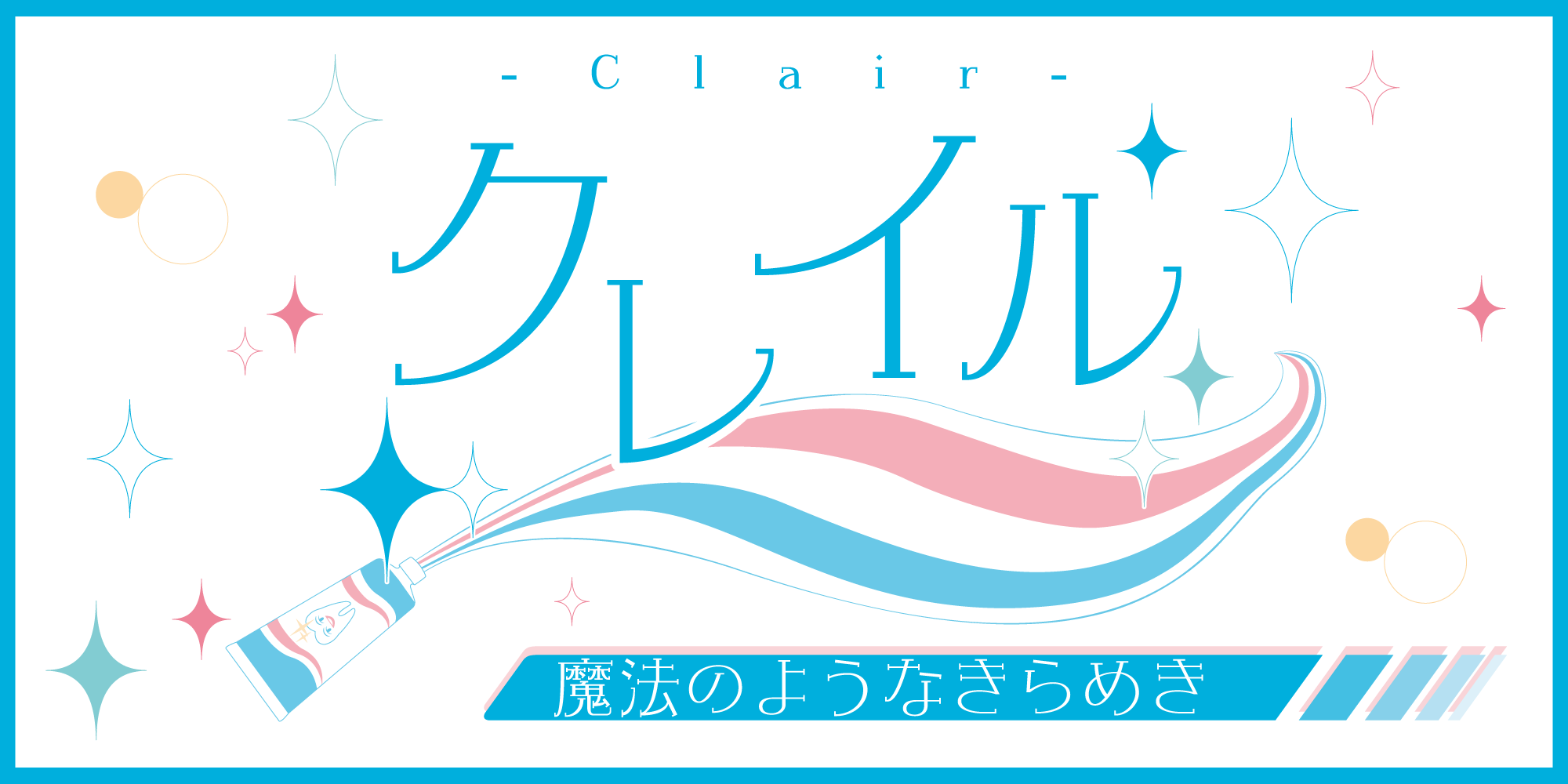
Monotype株式会社は、年間定額制フォントサービス「LETS Leading Edge Type Solution」のライブラリ「モトヤ LETS」および「学生向けモトヤ LETS」、ならびにWebフォントサービス「FONTPLUS」にて、文字にツヤと光沢感を与えるデザイン書体「モトヤクレイル 4」の提供を開始しました。
モトヤクレイル コンセプト
モトヤクレイルは、文章に「ツヤ」「光沢感」を付与できるデザイン書体です。その性質から、書体名にはフランス語で「明るい」「光」を意味する「Clair(クレイル)」と名付けました。
文字のバランスは全て足長気味にデザインし、あえて重心を高めに設定しています。
モトヤクレイルは、文字の表情として「清潔感」「高級感」を持ち合わせているため、例えば清掃用品・歯科衛生用品・洗車グッズのパッケージやロゴ、美容室・サロンの看板やキャッチコピーへの使用にも最適です。モトヤクレイル2、モトヤクレイル4の2ウェイトございます。
モトヤクレイル 4 Std